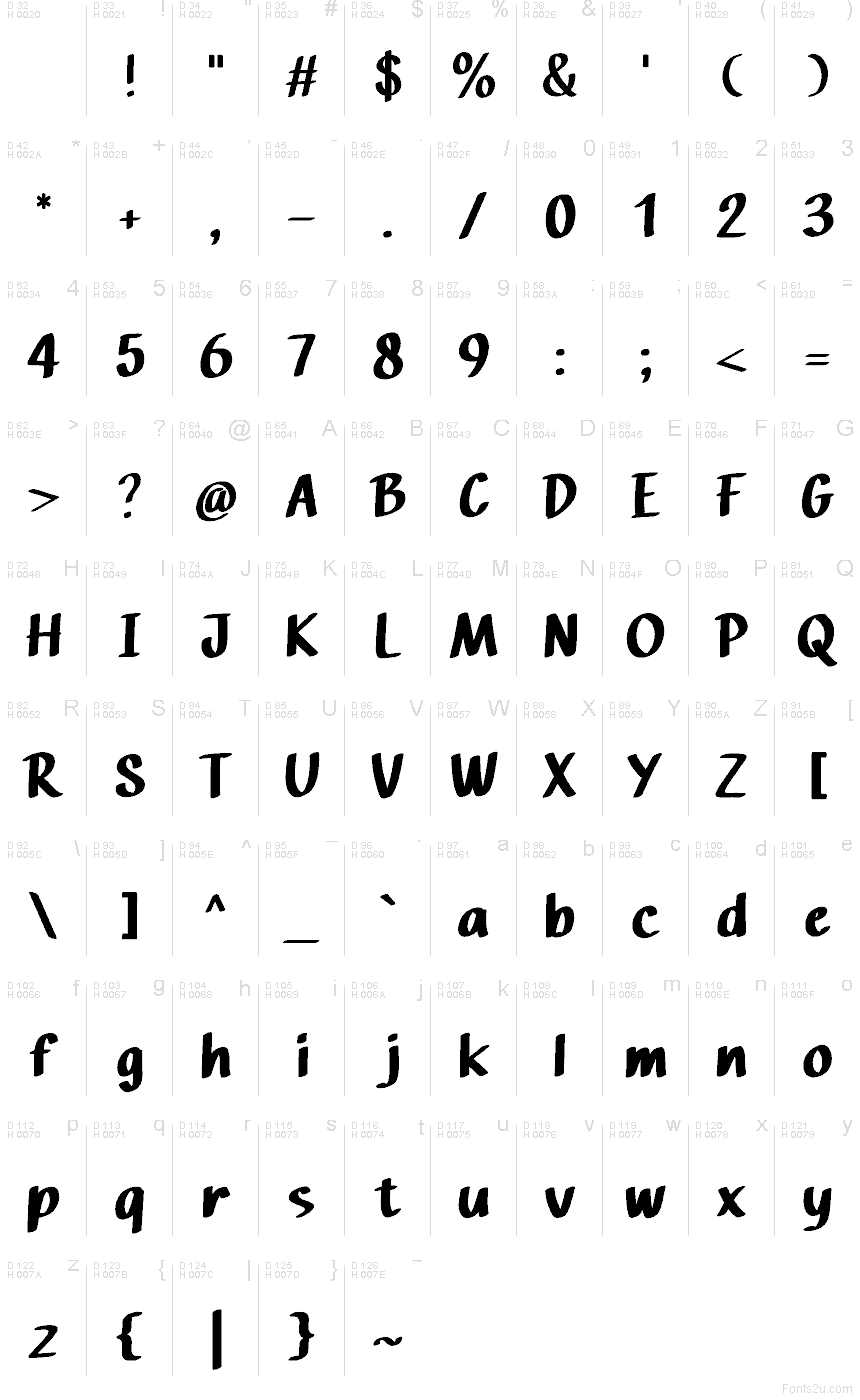
Summer Short
Summer Short від Hello Good Studio — це безкоштовний рукописний шрифт із плавним ритмом, що нагадує мазки пензлем, та заокругленими, злегка нахиленими формами. Літери поєднуються невимушено, з м’якими вигинами та широкими штрихами, що надає йому вигляду живого рукописного нотатника, а не формального каліграфічного стилю.
Summer Short чудово підходить для запрошень на пляжні вечірки, сезонних логотипів, пакування товарів, графіки для соцмереж та листівок із цитатами. Цей безкоштовний шрифт додає індивідуальності та «ручного» шарму коротким словам і заголовкам, особливо коли ви хочете створити неформальний та легкий настрій.